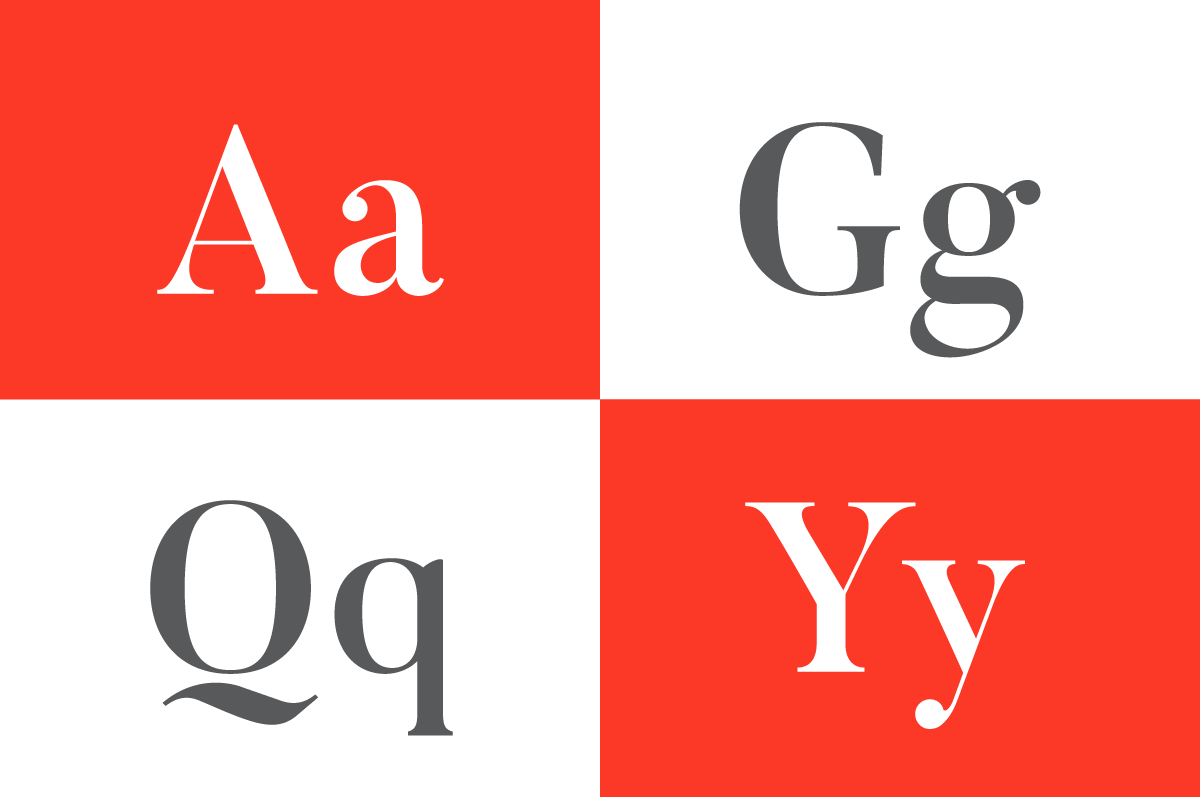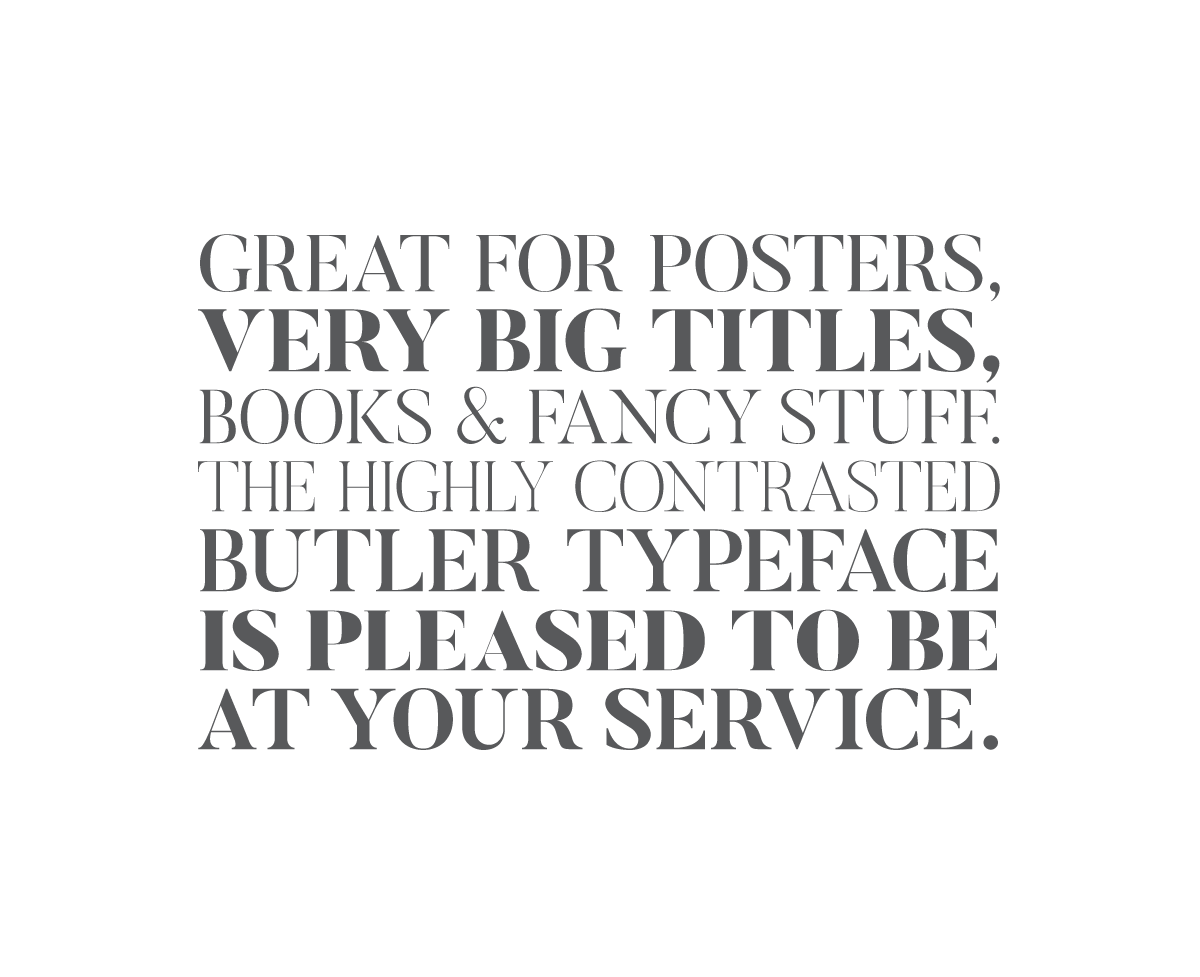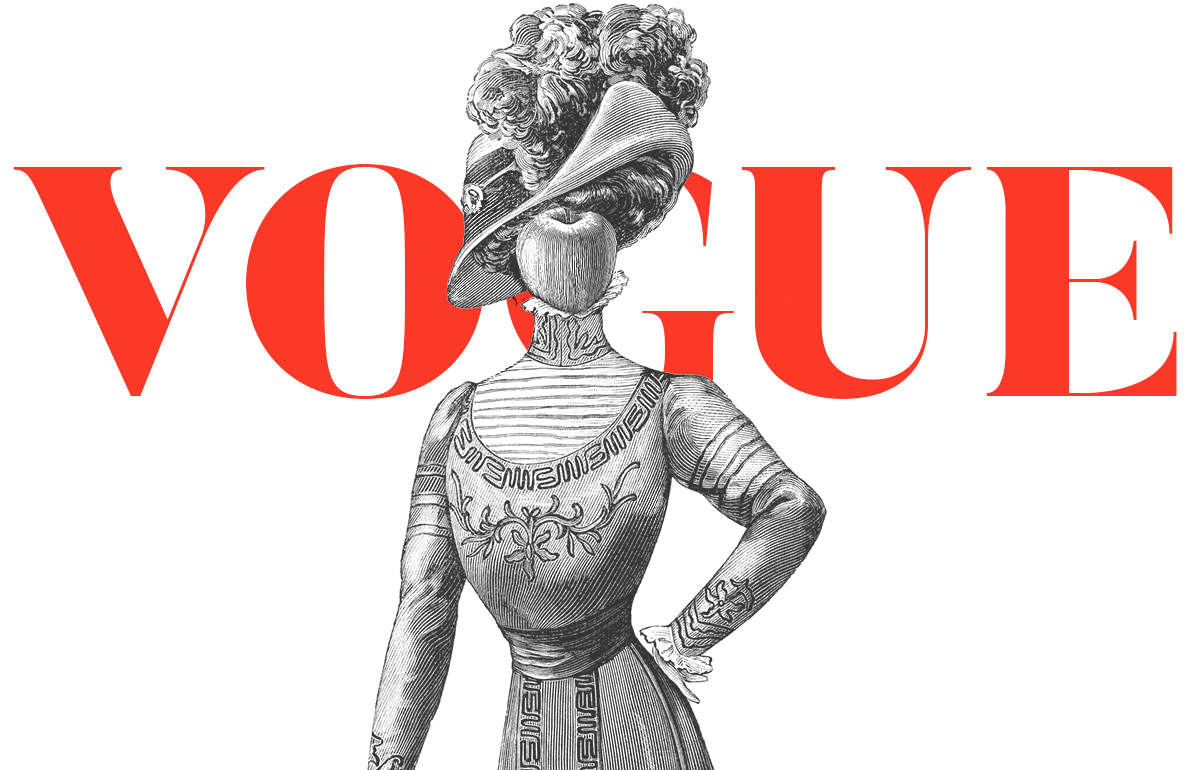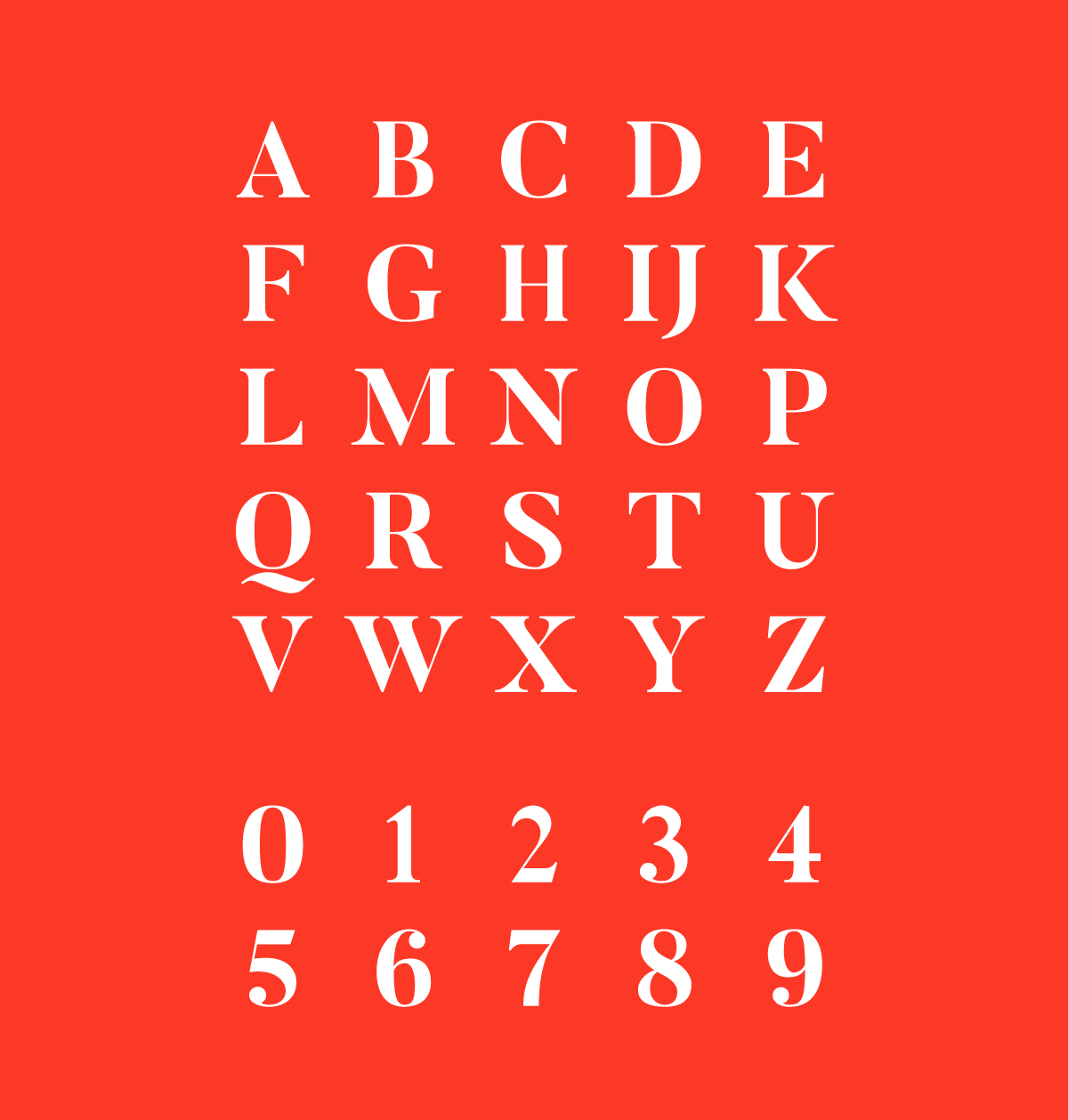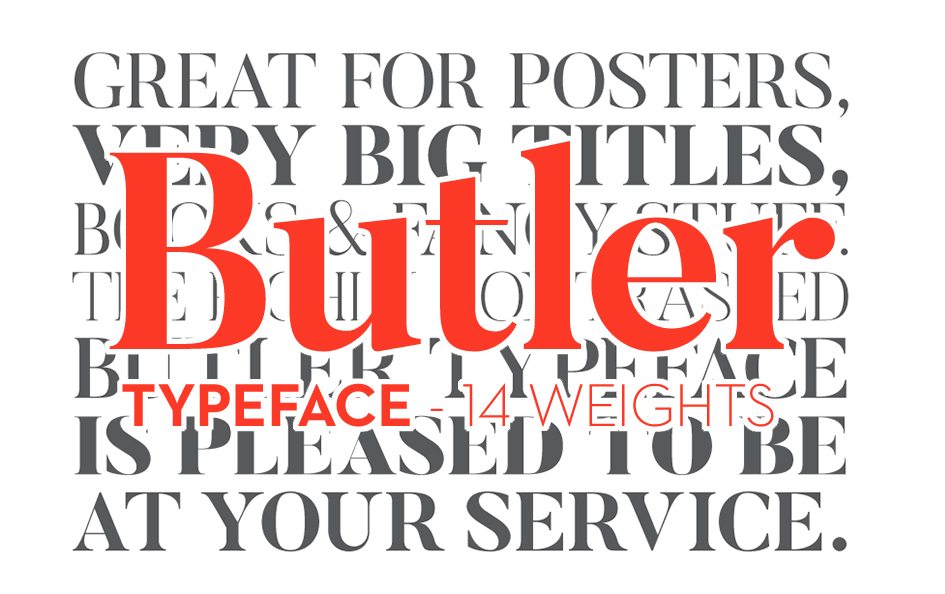
Font del giorno:Butler
il font che vi presentiamo oggi é:Butler
Butler è un carattere serif gratuito che mescola il Dala Floda e la sorprendente famiglia Bodoni. L’obiettivo principale era quello di portare un po ‘di modernità ai caratteri serif lavorando sulle curve di font serif classici e e aggiungendo una famiglia stencil in più.
ottimo per i manifesti, utilizzabile per grandi titoli, libri, il carattere tipografico  è un vero e proprio maggiordomo (butler) è lieta di essere al vostro servizio.
Tutta la famiglia Butler contiene un totale di 334 caratteri, 7 pesi regolari e 7 pesi stencil, figure di testo, legature, frazioni e molto di più. Si adatta anche molte lingue diverse, con i suoi glifi aggiuntivi.